㈜윤디자인-스틸러, 아이웨어 콜라보 제품 12일 정식 판매
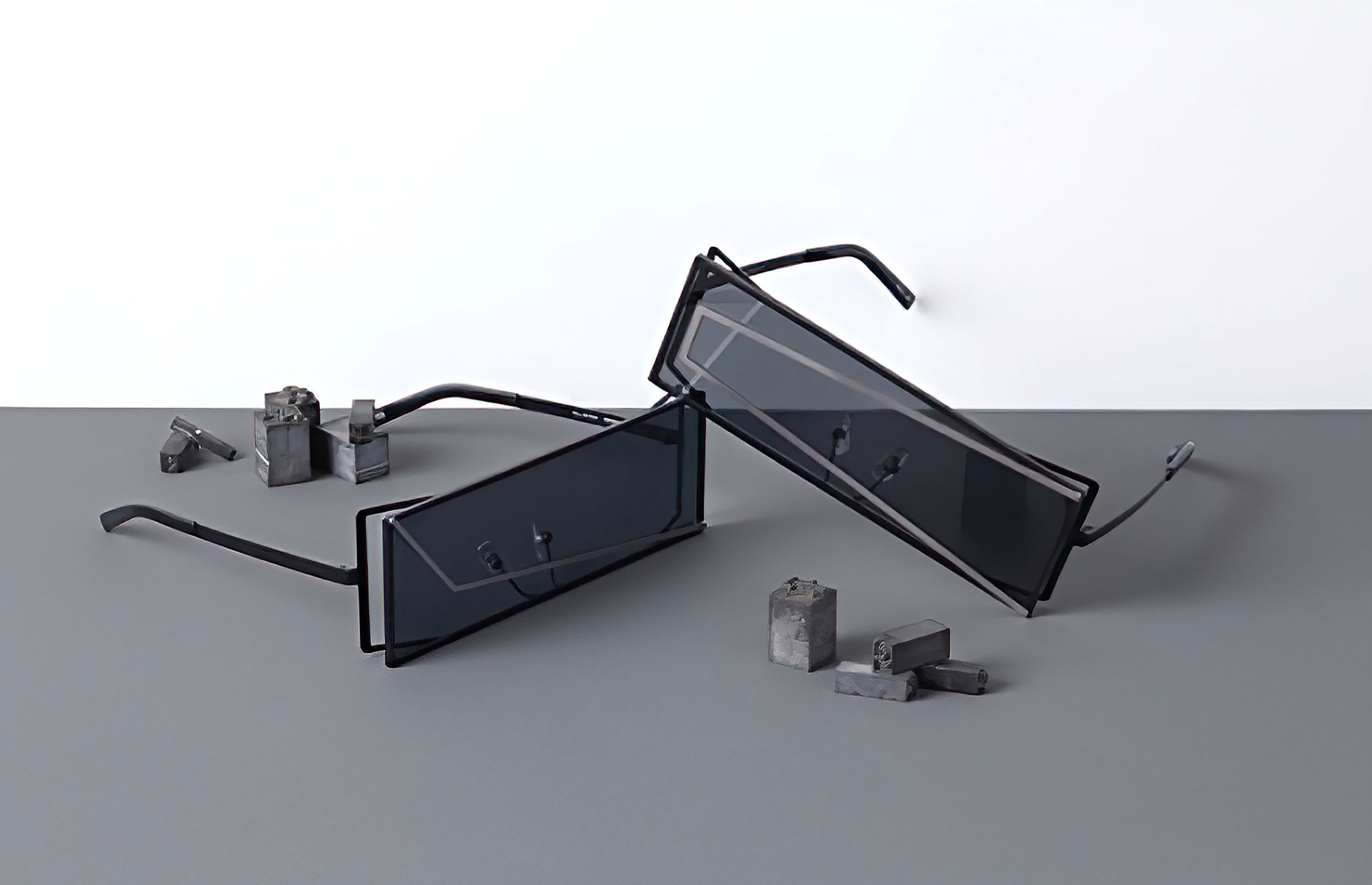
㈜윤디자인-스틸러 콜라보레이션 제품 '뮤지크 크리에이티브 레이블(MUZIK CREATIVE LABEL)'
유니크한 디자인, 최상의 제품 퀄리티, 다양한 프로젝트 전개로 유명한 글로벌 아이웨어 브랜드 스틸러와 혁신적인 디자인으로 한글 문화를 선도하는 디자인 전문기업 ㈜윤디자인그룹이 디지털 폰트 윤명조와 윤고딕을 테마로 한 아이웨어 콜라보레이션 제품을 12일 정식 판매한다고 밝혔다.
지난 10월 9일 한글날 양사의 제휴를 공개한 이후 각 분야에서 독보적인 영역을 구축하며 많은 마니아층을 보유하고 있는 두 브랜드의 만남에 소비자들의 관심이 집중돼 왔다.
'쓰고, 쓰다(WRITE&WEAR)'라는 컨셉으로 진행된 이번 콜라보레이션은 아이웨어와 글자라는 전혀 다른 카테고리이지만 아이웨어를 쓰고 글자를 쓰는 것에 대한 두 브랜드의 접점과 스틸과 한글이라는 소재의 무한한 확장성을 다루는 두 브랜드의 크리에이티브한 발상을 고스란히 담아냈다.
콜라보레이션 제품은 총 4가지 아이웨어 모델로 구성되었으며, 제품에 한글을 형상화해 누구나 손쉽게 쓰는 아이웨어에 한글의 아름다움을 담았다. 유니크한 디자인이 돋보이는 모델과 더불어 데일리 아이템은 물론 라이프스타일에 맞춰 활용할 수 있는 모델을 함께 선보였다. 또한 이를 다양한 방식으로 표현한 아트웍을 통해 두 브랜드의 아이덴티티를 강조하고 있다.
특히 이번 콜라보레이션 제품은 국내뿐 아니라 해외 박람회에서도 공개되어 국내외 많은 전문가들의 호평을 받았으며 시각적으로 위트있게 조합한 그래픽도 한글의 우수한 미감을 널리 알리는데 공헌했다는 평가를 받고 있다.